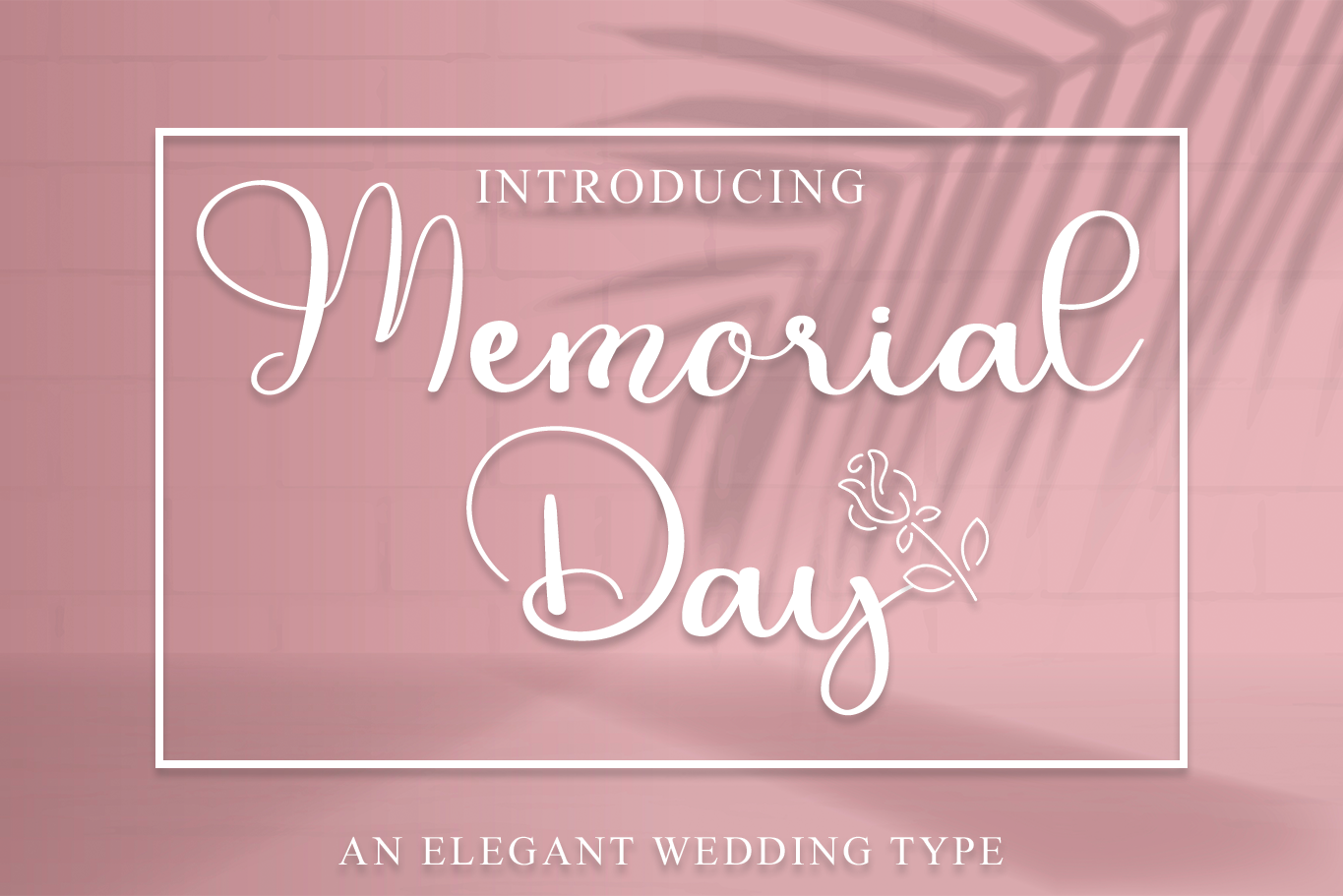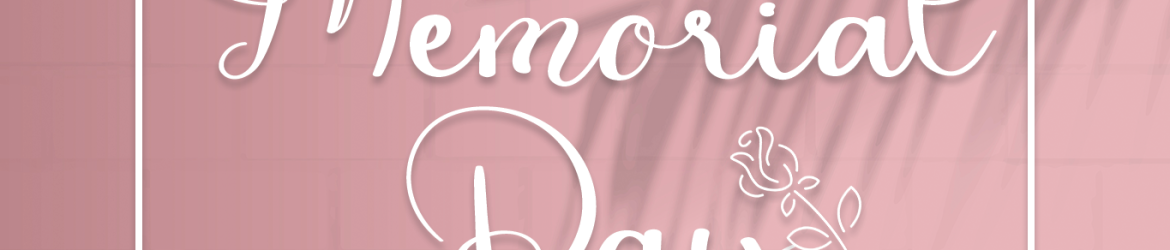
Memorial Day Font – Download Grátis
Esta fonte é perfeitamente desenhada para quem busca um estilo elegante que se destaca nos mais diversos ambientes de design. Ela transmite uma sensação encantadora e sofisticada, combinando elementos clássicos com uma leve modernidade, o que a torna ideal para diversas aplicações. Seja em invitações de casamento, cartões de agradecimento, citações ou cartões de cumprimentos, esta fonte traz um toque autêntico e pessoal às criações. Além disso, é perfeita para assinaturas de logotipos, cartões de negócio e qualquer outro projeto que seja beneficiado por uma marca registrada e elegante. A Memória Day Font é uma escolha inteligente para designers em busca de personalidade e sofisticação em suas criações visuais.